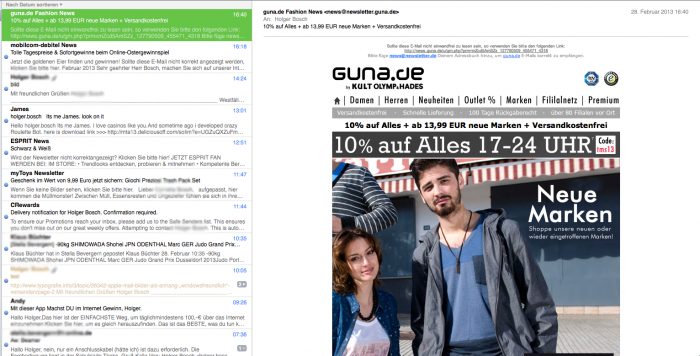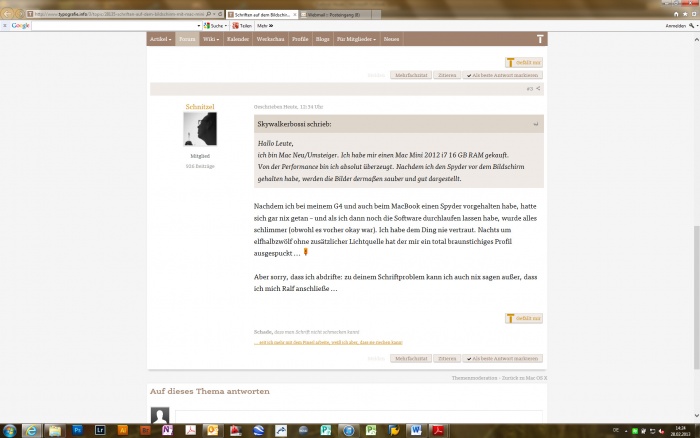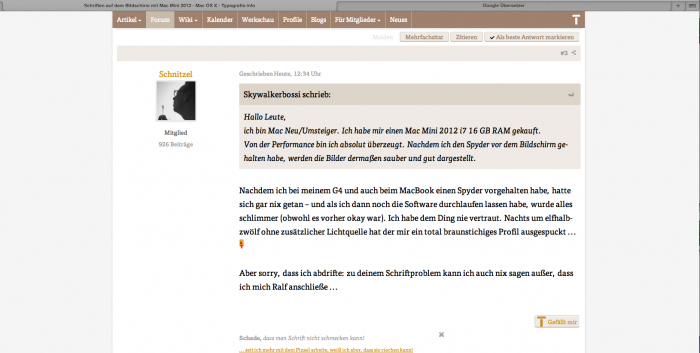
Schriften auf dem Bildschirm mit Mac Mini 2012
ich bin Mac Neu/Umsteiger. Ich habe mir einen Mac Mini 2012 i7 16 GB RAM gekauft.
Von der Performance bin ich absolut überzeugt. Nachdem ich den Spyder vor dem Bildschirm gehalten habe, werden die Bilder dermaßen sauber und gut dargestellt. Photoshop, InDesign und Lightroom laufen super. Einzig die Darstellung der Schrift ist grausig. Ich habe schon viel ausprobiert: Bildschirm Wechsel, Schriftenglättung usw.
Auf einem iMac ist alles super. Ist es ein Mac Mini Problem. Hat schon mal jemand von euch davon gehört??
»Grauselig« ist nicht wirklich eine Fehlerbeschreibung. Wir bräuchten eine bessere Beschreibung oder Screenshots/Fotos.
In welchem Programmen tritt das auf? In welchen Größen? Wie äußert sich die »grauselige Darstellung«?
Wurde für das Display die native Größe in den System-Einstellungen von OS X ausgewählt?
Nachdem ich bei meinem G4 und auch beim MacBook einen Spyder vorgehalten habe, hatte sich gar nix getan – und als ich dann noch die Software durchlaufen lassen habe, wurde alles schlimmer (obwohl es vorher okay war). Ich habe dem Ding nie vertraut. Nachts um elfhalbzwölf ohne zusätzlicher Lichtquelle hat der mir ein total braunstichiges Profil ausgespuckt ...  :neenee:
Aber sorry, dass ich abdrifte: zu deinem Schriftproblem kann ich auch nix sagen außer, dass ich mich Ralf anschließe ...
ich werde später mal Screenshots senden..sitze im Augenblick vor einem Windows PV :-). Mit "grausig" meine ich "verwaschen" "unscharf". In vielen Foren ließt man, dass das so bei Apple wäre, man müsse sich daran gewöhnen. Das ist aber quatsch. Am iMac ist die Schrift scharf. Und auch Apple hat mir an der Hotline versichert, dass es nicht OK ist, konnte aber auch keine Lösung anbieten. Mir wurde umgehend ein neuer Mac Mini zu geschickt..der Service ist schon Klasse! Leider empfinde ich es immer noch so...
Hast Du die Kantenglättung aktiviert? Die kannst Du noch ein bischen feiner einstellen, wenn auch nicht so gut wie unter Windows. Zudem funktioniert das Kantenglätten unter Windows anders als unter OSX, da kommt noch ein Gewöhnungsfaktor hinzu.
hier mal Screenshots von Windows und Mac..ihr wißt welches Bild wohin gehört. Dann ein Screenshot aus Mac Mail..dort finde ich es am schlimmsten. Schaut es euch an, und sagt mir eure Meinung.
Dann direkt noch eine Frage, was ist denn eine gute Schriftart unter Mac, die dann nicht auf einen Standard Windows PC in Times New Roman verändert wird?
Georgia. Ist sowieso die <vorurteil>bessere Anzeigeschrift im Netz als die Times in ihren Varianten</vorurteil>.
Und auf diesen zur Unleserlichkeit skalierten Bilder sind nicht aussagekräftig.
Womit hast Du denn deinen Bildschirm kalibriert?
Es geht um die Schriftdarstellung auf dem Bildschirm  :huhu:
Ja, aber die Bilder werden ja eine andere Ur-Auflösung haben (1920*1080 oder sowas). Wenn Du das hier anhängst, werden sie auf 400*600 (oder was auch immer) rungerechnet und so ist die Schriftendarstellung jenseits des Grauwertes nicht mehr erkennbar.
Das ist schon ein paar Jahre her, das müsste dieses Spyder2irgendwas-Gerät an einem SiemensFujitsu-Display gewesen sein. Danach habe ich es aufgegeben und mir gesagt, dass für die tägliche Arbeit das Standardprofil absolut ausreichend ist ...